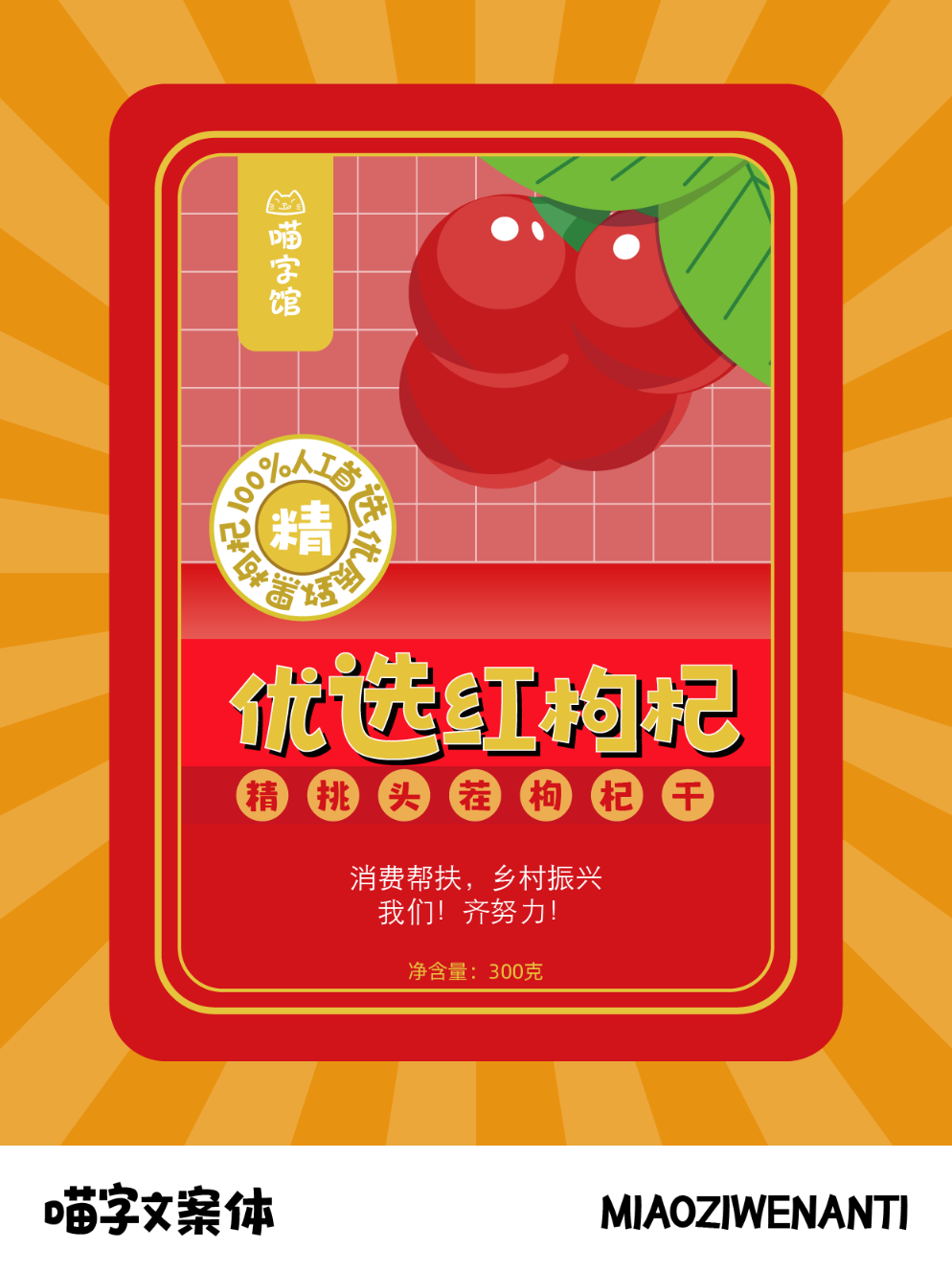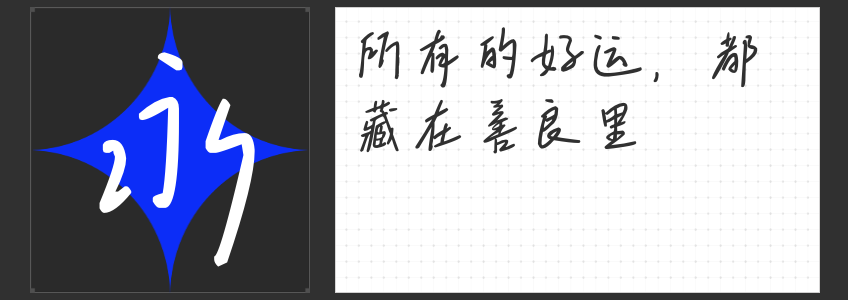
字体之美,文创之魂:四款精选字体推荐
在文创产品的设计中,字体不仅是信息传递的载体,更是情感与风格的直观表达。恰当的字体选择,能让作品瞬间生动起来,直击人心。今天,就为大家精选四款各具特色的字体,为你的文创设计增添无限灵感。
1. 励字开拓者简 超黑:未来感的笔触探索
这款字体以其独特的直线笔画设计脱颖而出,横平竖直,棱角分明,简约而不失力量感。它仿佛是现代科技与未来世界的视觉语言,适用于追求前卫、科技感十足的文创产品设计。无论是电子产品的包装,还是未来主题的艺术展览,都能通过“励字开拓者简 超黑”展现出独特的未来魅力。
2. 造字侠醉春风简繁 苍劲:传统韵味的灵动演绎
当传统遇上创意,“造字侠醉春风简繁 苍劲”以其自由率真、活泼灵动的姿态,为文创产品注入了浓厚的文化气息。其点画圆润,结构周正而不失松弛,特别适合用于书法、茶文化、传统节日等具有深厚文化底蕴的文创设计,让每一件作品都洋溢着古典与现代交织的美感。
3. 喵字文案体:萌趣可爱的文字艺术
提到可爱,怎能不提“喵字文案体”?这款字体专为萌系文创设计而生,圆润的线条、俏皮的字形,仿佛每一个字符都在诉说着温馨与欢乐。无论是儿童绘本、宠物用品,还是甜品店的菜单设计,都能通过“喵字文案体”轻松营造出温馨可爱的氛围,让人爱不释手。
4. 也字工厂绮梦手迹:随性慵懒的生活美学
在快节奏的现代生活中,“也字工厂绮梦手迹”以其独有的慵懒随性感,为我们带来一丝宁静与惬意。这款字体笔画复杂与简单交织,却和谐共生,不显疏离。它适合用于旅行日记、家居装饰、手账记录等追求自然、随性风格的文创产品,让每一次书写都成为一场关于生活的绮丽梦境。
选择适合的字体,就是选择了一种情感表达的方式。以上四款字体,各具特色,总有一款能触动你的心弦,为你的文创产品设计增添无限可能。